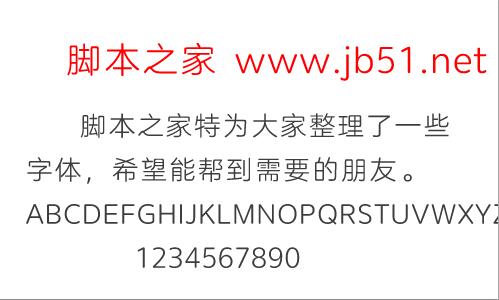
漢儀正圓45S是由漢儀字庫(kù)出品的一款電腦中文字體,該字體書(shū)寫(xiě)簡(jiǎn)潔工整,形態(tài)端正大方,同時(shí)全面支持中英文、阿拉伯?dāng)?shù)字等等,適合應(yīng)用于藝術(shù)設(shè)計(jì)、平面宣傳設(shè)計(jì)、網(wǎng)頁(yè)設(shè)計(jì),書(shū)法字帖等領(lǐng)域,也可以應(yīng)用于文本裝潢、信息展示、篆刻制模英文、數(shù)據(jù)制作、裝潢設(shè)計(jì)、視覺(jué)設(shè)計(jì)、字帖等一切合法應(yīng)用場(chǎng)景,有喜歡的朋友可免費(fèi)下載收藏。